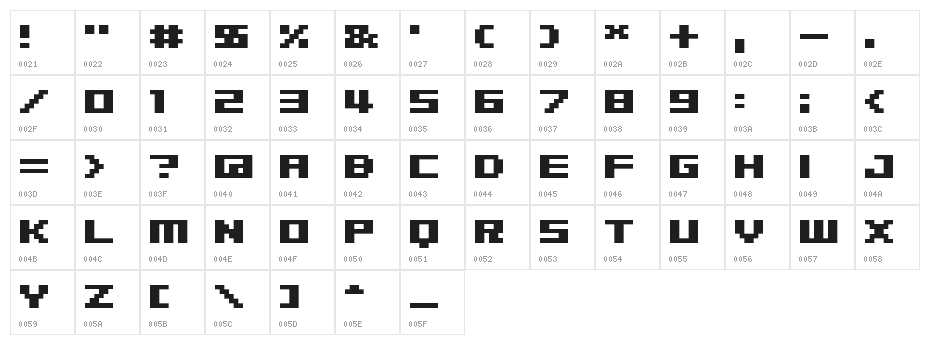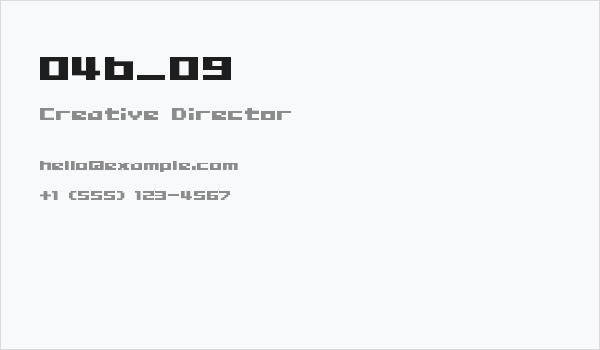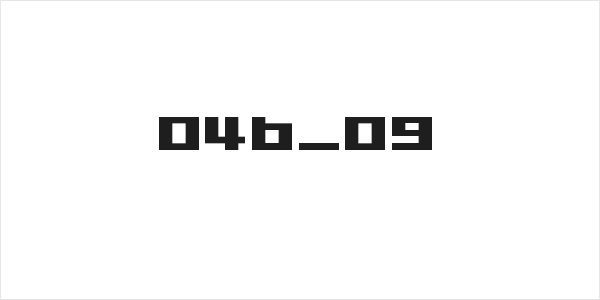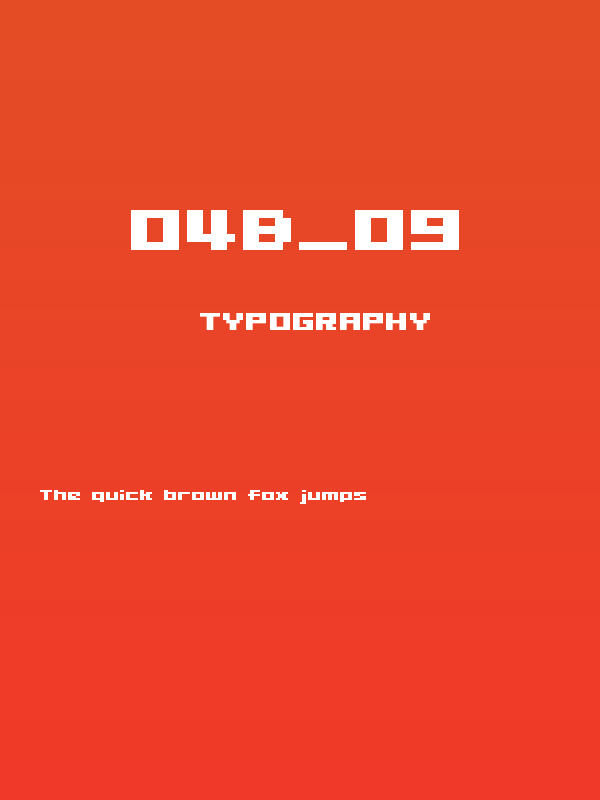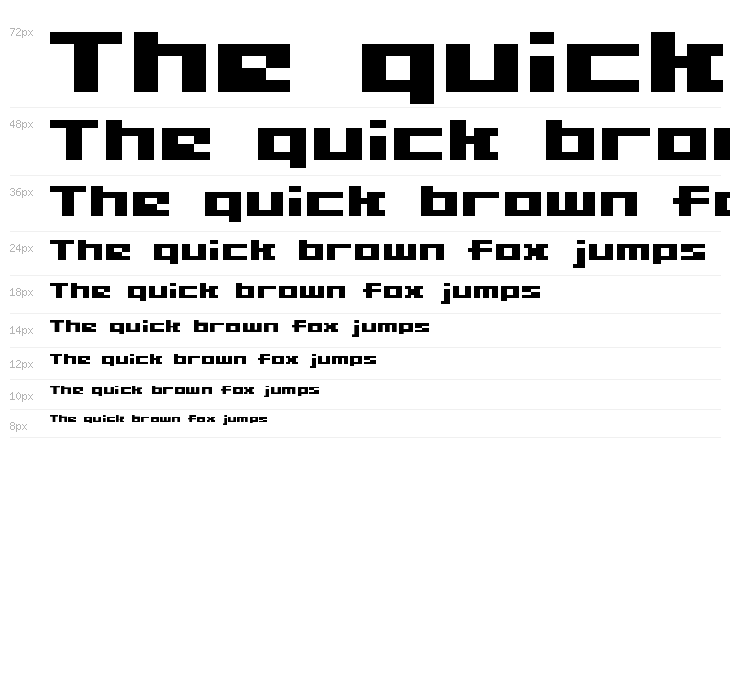
04b_09 Font
| Kategorien | Pixel |
| Gesamtstil | Retro, Digital |
| Anwendungsfall | Headlines, Logos, Digital displays |
| Vorgeschlagene Projekte | Ideal for video game design, retro-themed graphics, digital art projects, and any creative work that seeks to evoke nostalgia for early computing and gaming eras. |